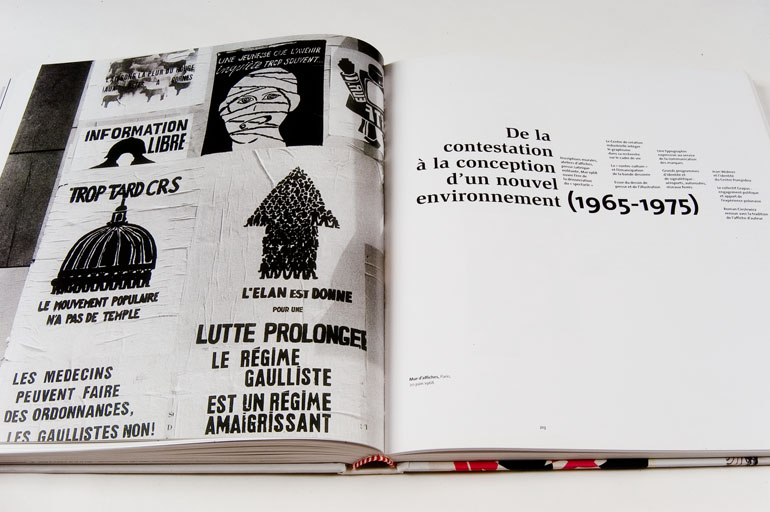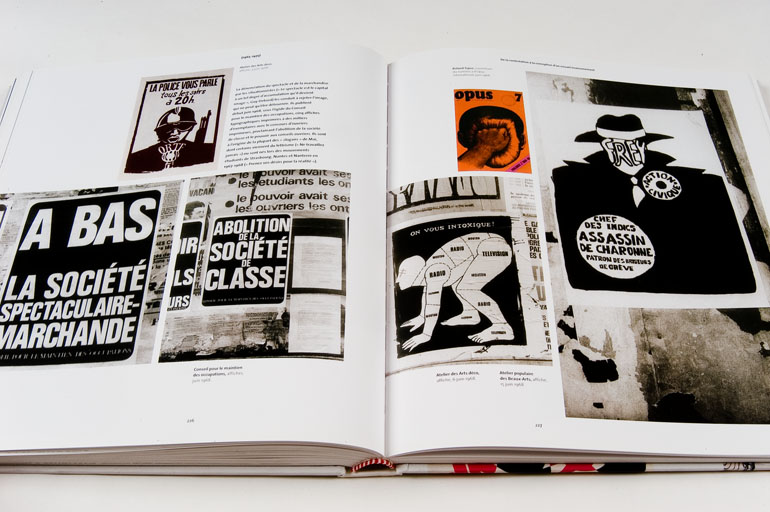
Mai 68, analyse des Signes précurseurs | demain 21 mai à 18h30
et rencontrer Michel Wlassikoff qui nous conte
l’«Histoire du graphisme en France»
séance spéciale
exposant sa recherche
sur les signes de Mai 68
Michel Wlassikoff conclura son cycle de conférences sur l’histoire du graphisme par une séance spéciale exposant sa recherche sur les signes de Mai 68. Il indiquera quelques signes avant coureurs du côté du mouvement situationniste ou de l’affiche cubaine, il commentera l’émergence des ateliers populaires et leur fonctionnement à partir de documents et témoignages inédits, enfin il s’attachera à définir l’« héritage » dans ce domaine.
Michel Wlassikoff vient de publier Mai 68 l’affiche en héritage aux éditions Alternatives, il est commissaire de l’exposition des affiches conservées à la Bibliothèque nationale de France, présentées sous le même intitulé «Mai 68 l’affiche en héritage» à la Galerie Anatome, jusqu’au 26 juillet 2008.